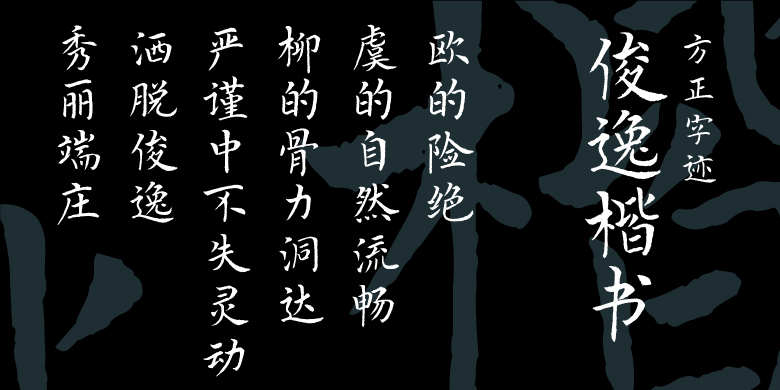
方正字迹-俊逸楷书
字体品牌: 方正字迹 设计师:谭太斌 字体分类:常规书写·毛笔 字体属性:精品字 字符集:大陆简体(GB2312-80)、简繁扩展(GBK) 发布时间: 2024
以欧楷为基础融合虞世南柳公权对传统书法进行了融合创新,取了欧的险绝,虞的自然流畅,柳的骨力洞达,严谨中不失灵动。洒脱俊逸,秀丽端庄。很适合现代排版,可以用于书籍,字帖,各种包装说明,装饰画,铭牌,广告标语等等。